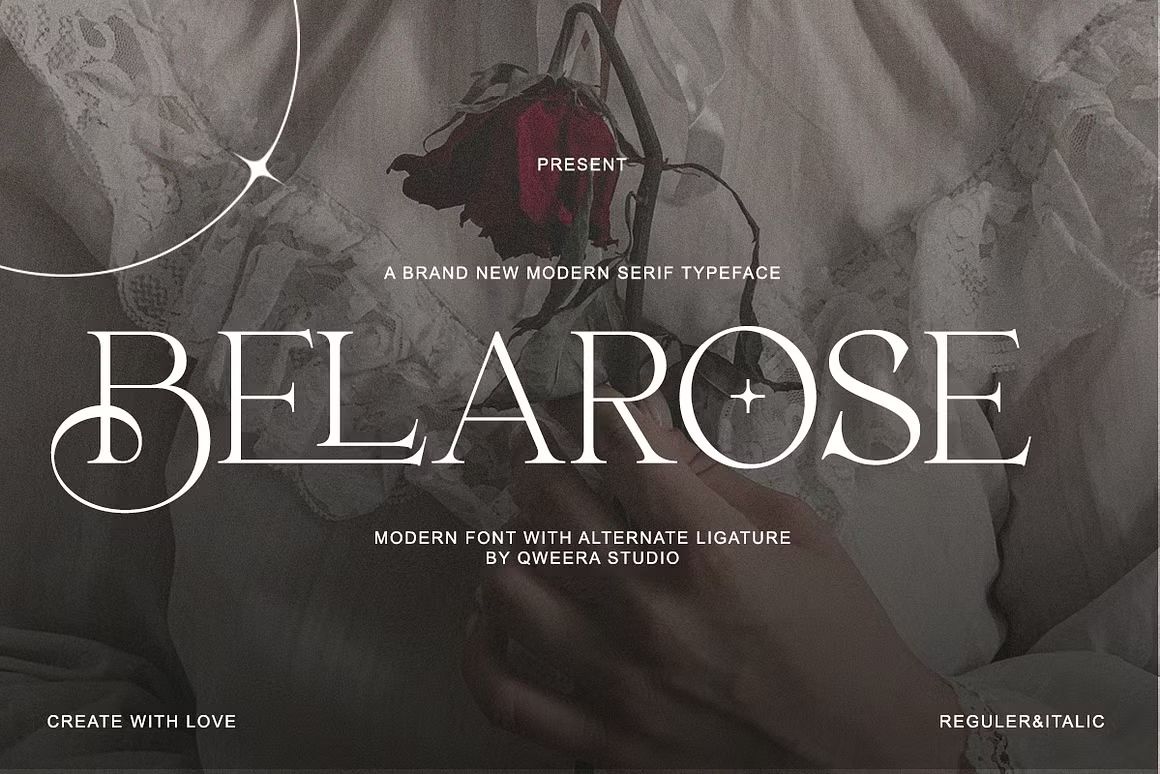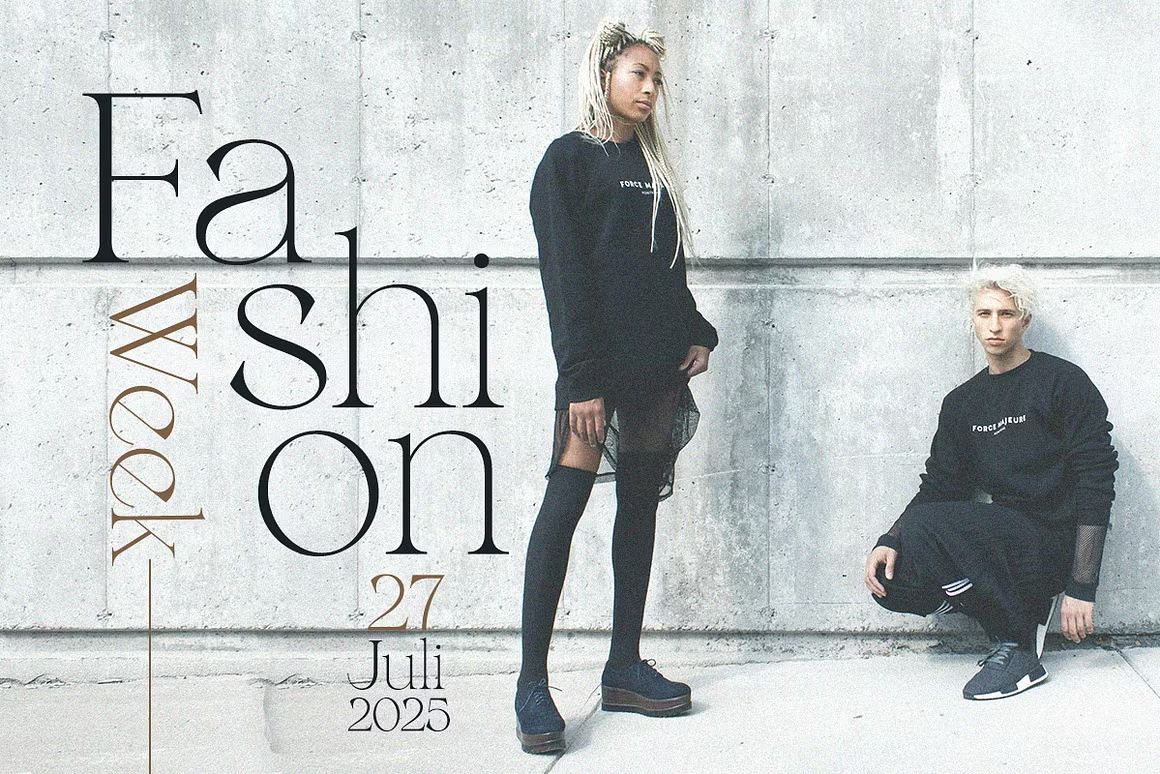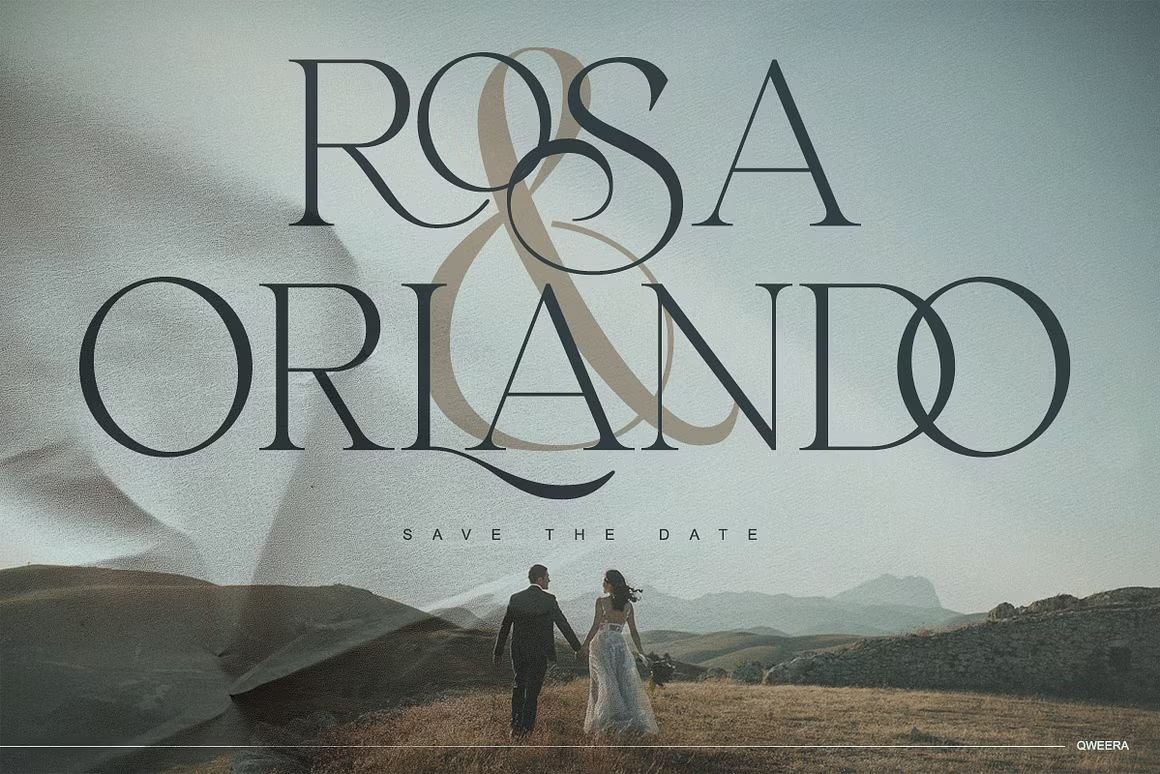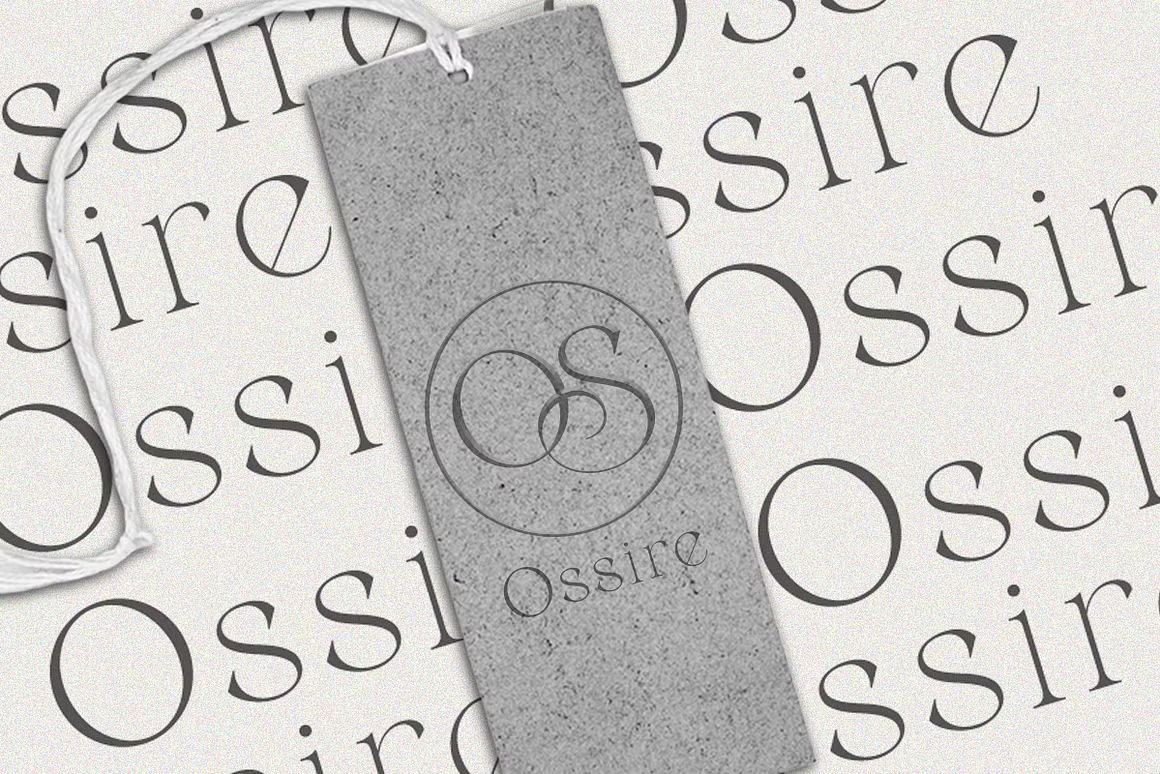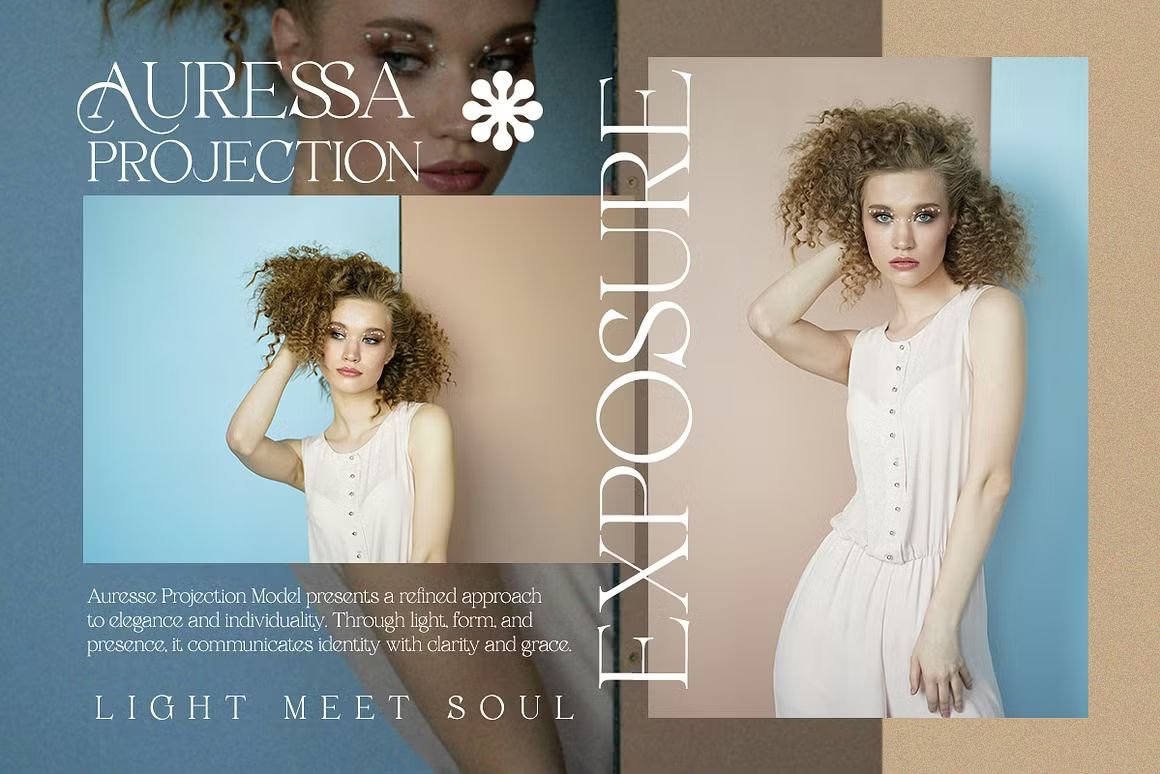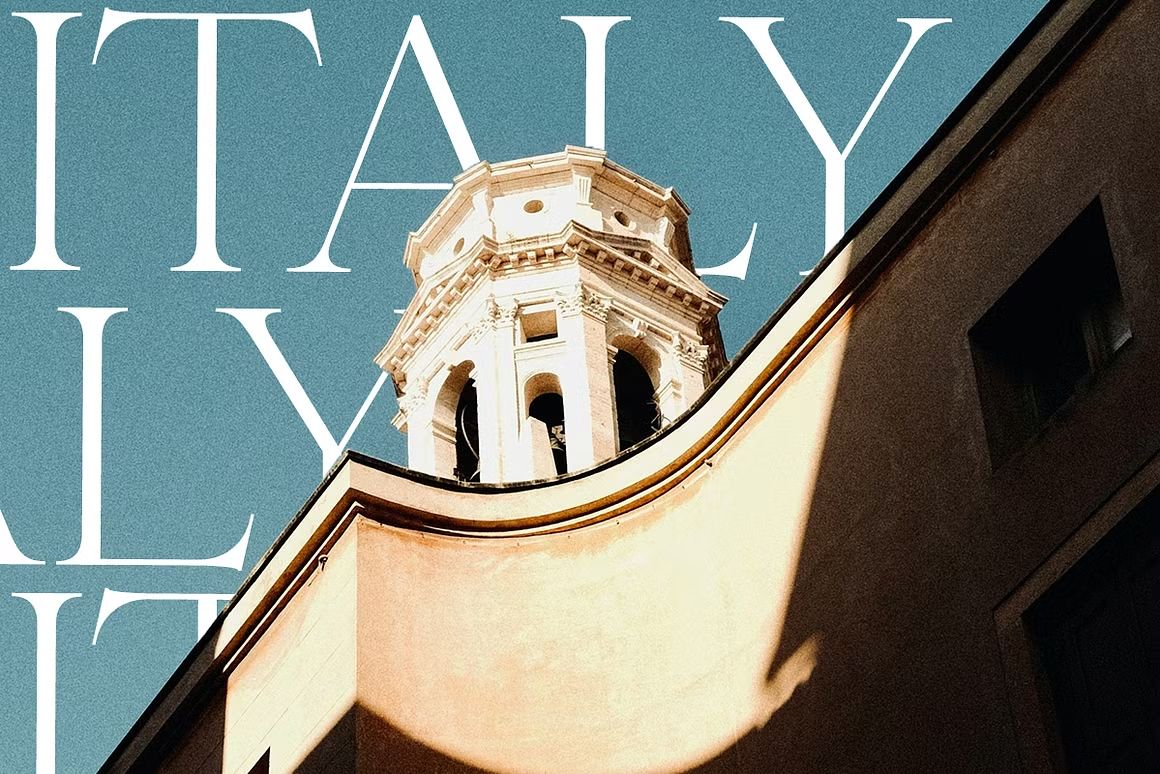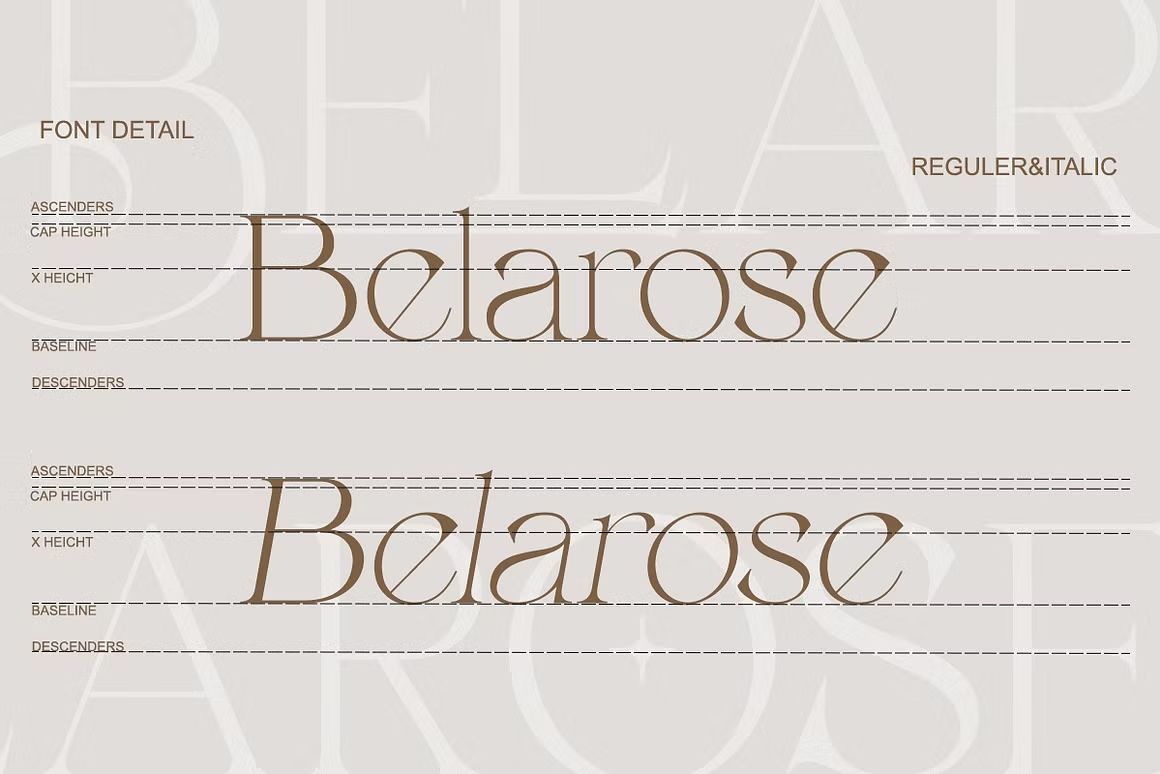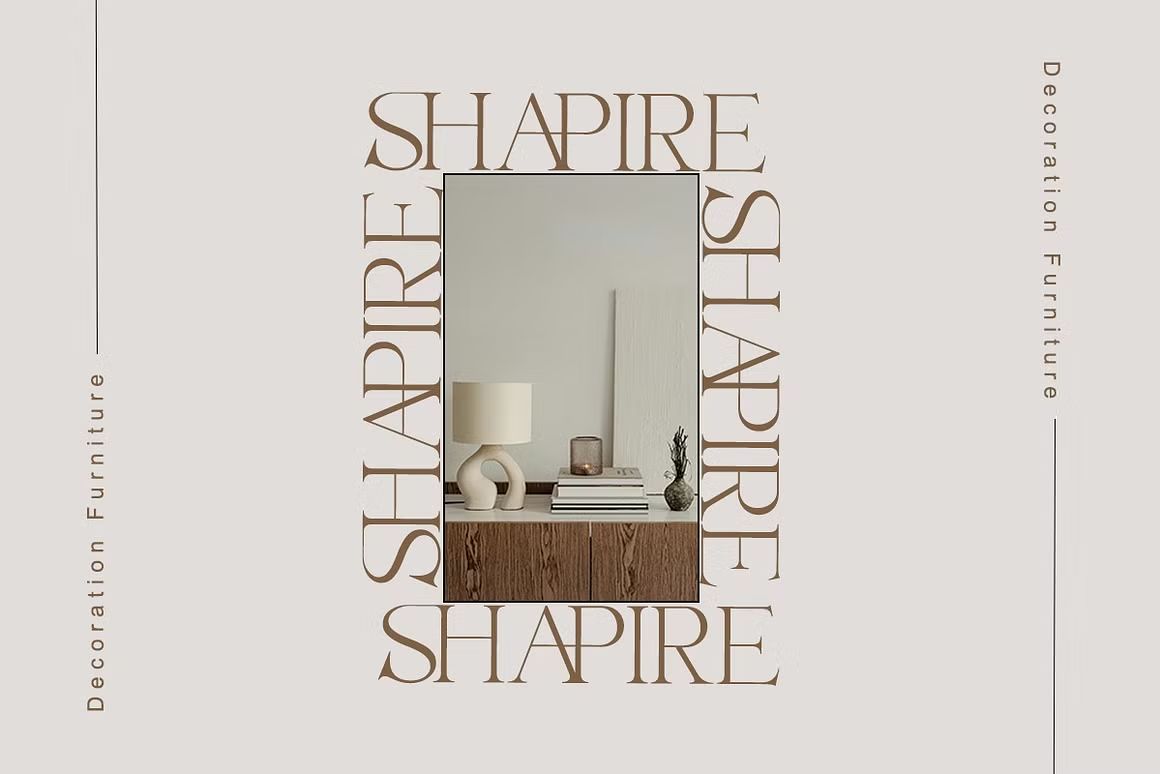
Belarose – Sans Serif Font
Belarose adalah font sans serif elegan dengan gaya modern dan feminin. Cocok untuk branding premium & desain fashion. Format OTF/TTF/WOFF, siap digunakan.
Belarose adalah font sans serif modern dengan sentuhan elegan dan feminin. Dengan bentuk huruf ramping, proporsi seimbang, dan tepi halus, font ini sangat cocok untuk branding kecantikan, logo fashion, editorial, undangan, dan kemasan produk premium. Belarose menghadirkan nuansa mewah yang tetap bersih dan minimalis.
• Sans serif ramping dan elegan
• Ideal untuk branding feminin, editorial, dan produk premium
• Termasuk huruf besar, kecil, angka, dan simbol